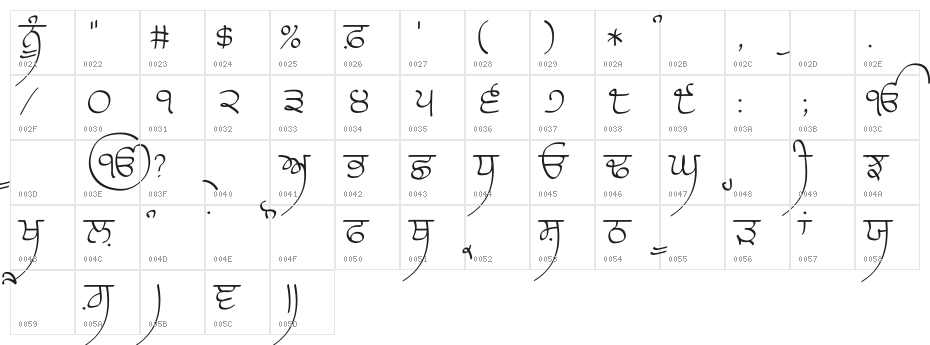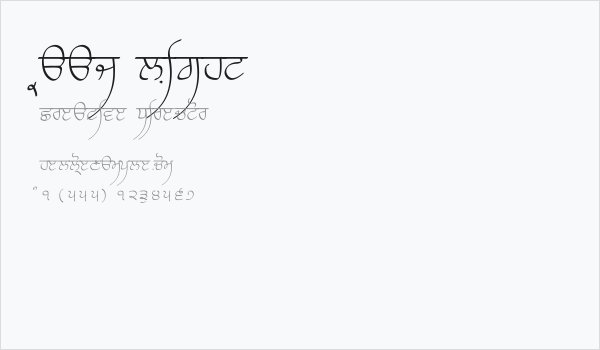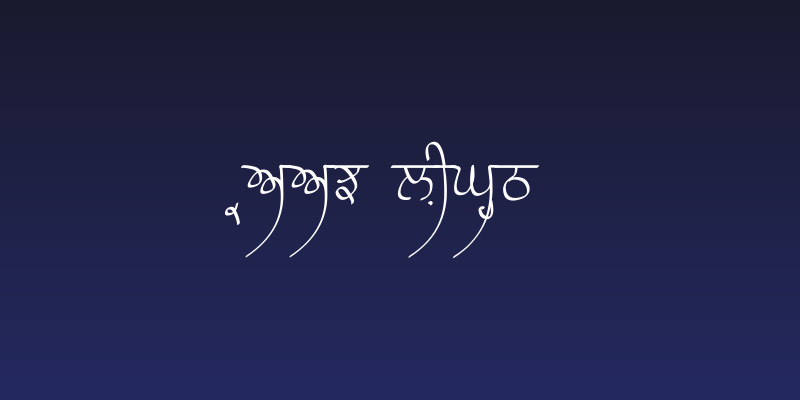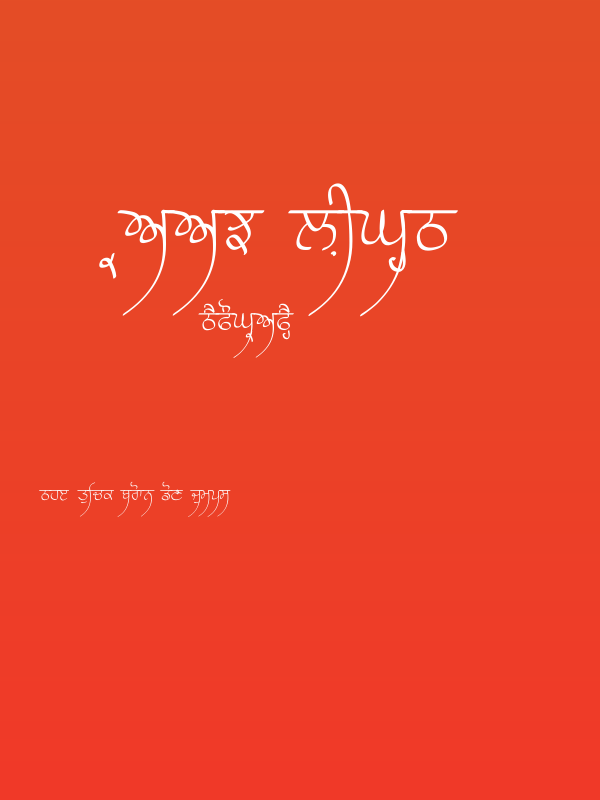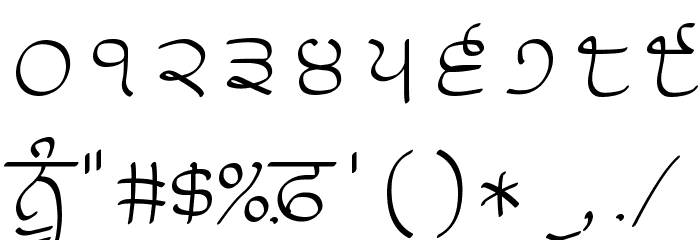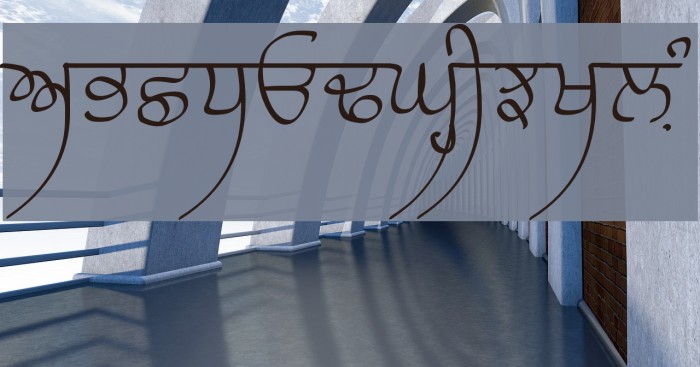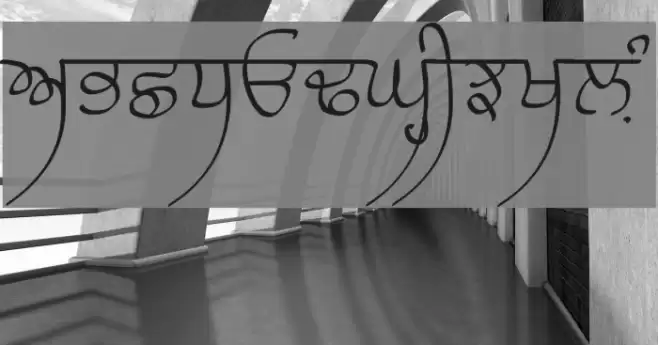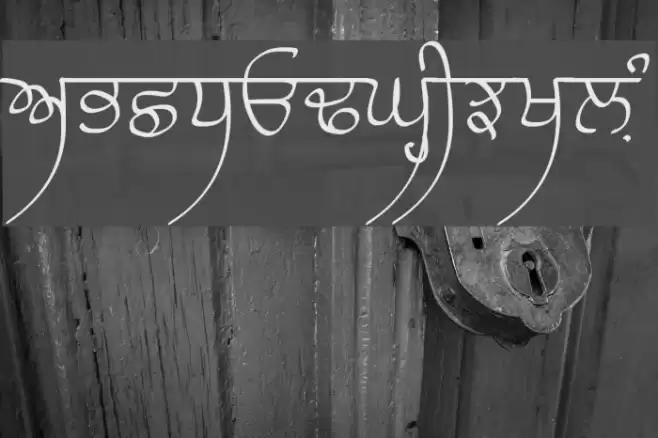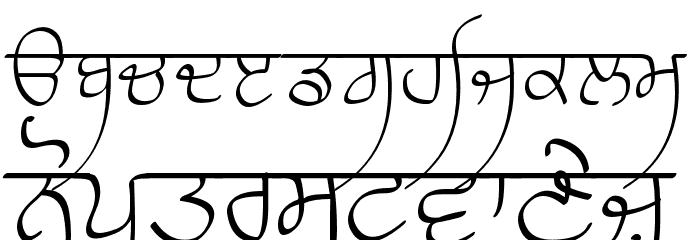
Raaj Light Font
| Gesamtstil | Traditional |
| Anwendungsfall | Headlines, Invitations, Cultural designs |
| Vorgeschlagene Projekte | Ideal for wedding invitations, cultural event posters, elegant branding, and traditional-themed designs. |